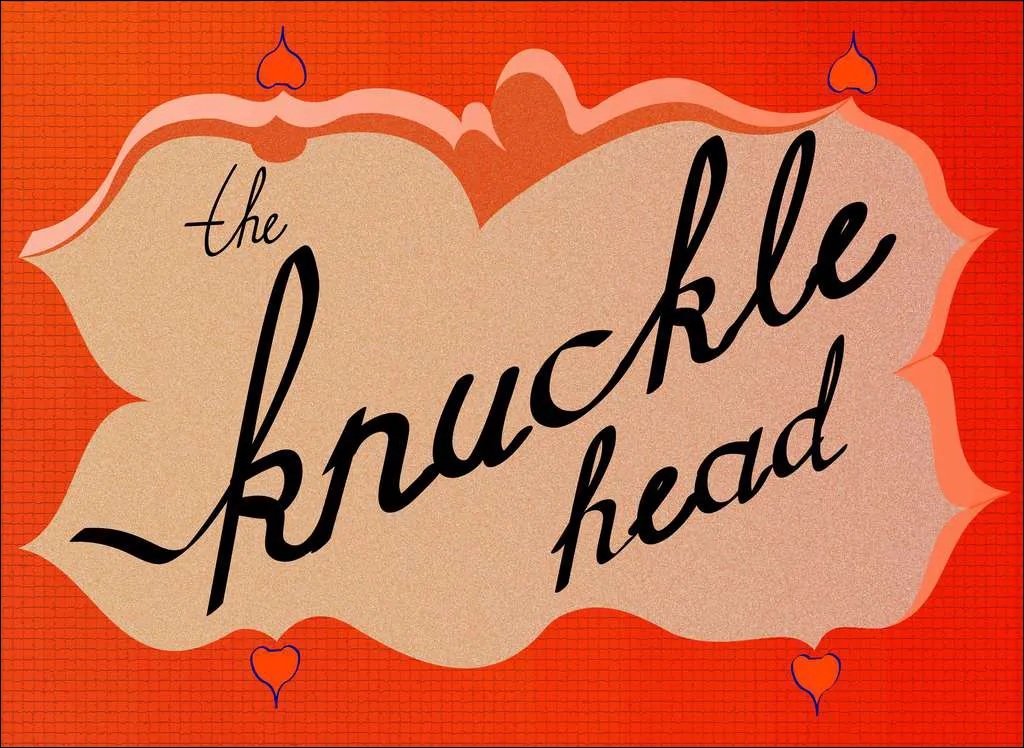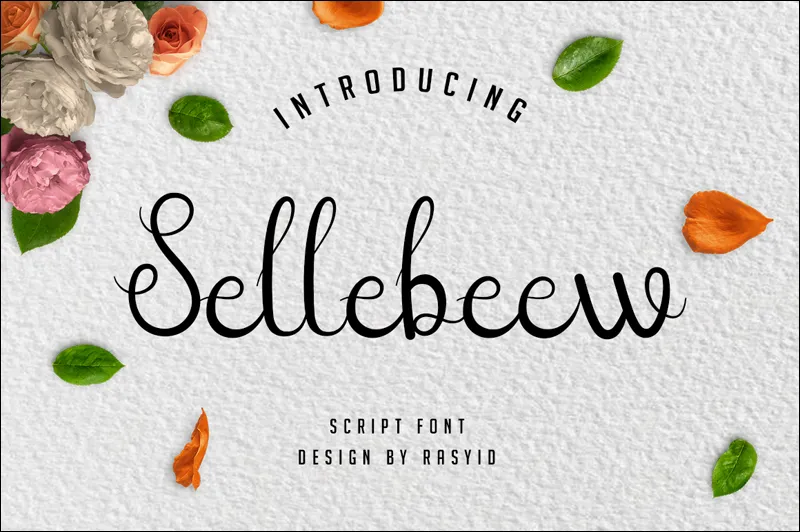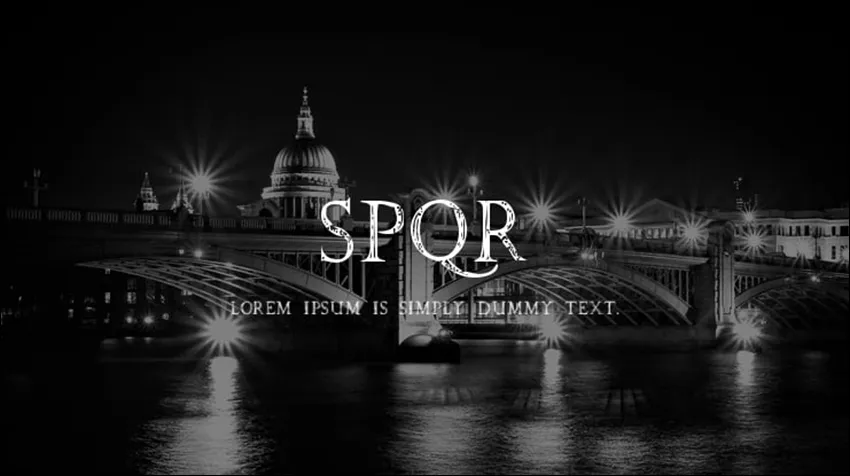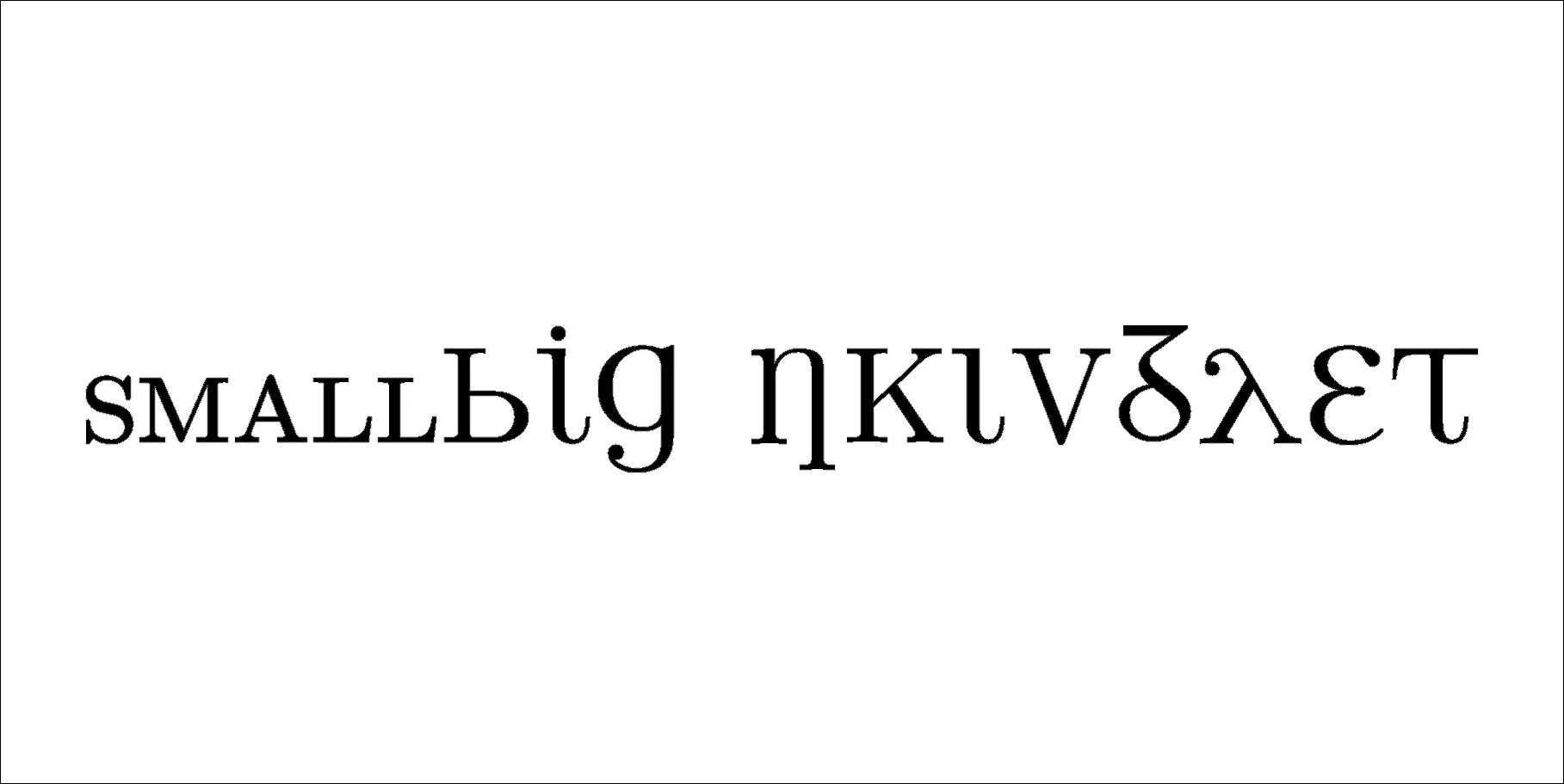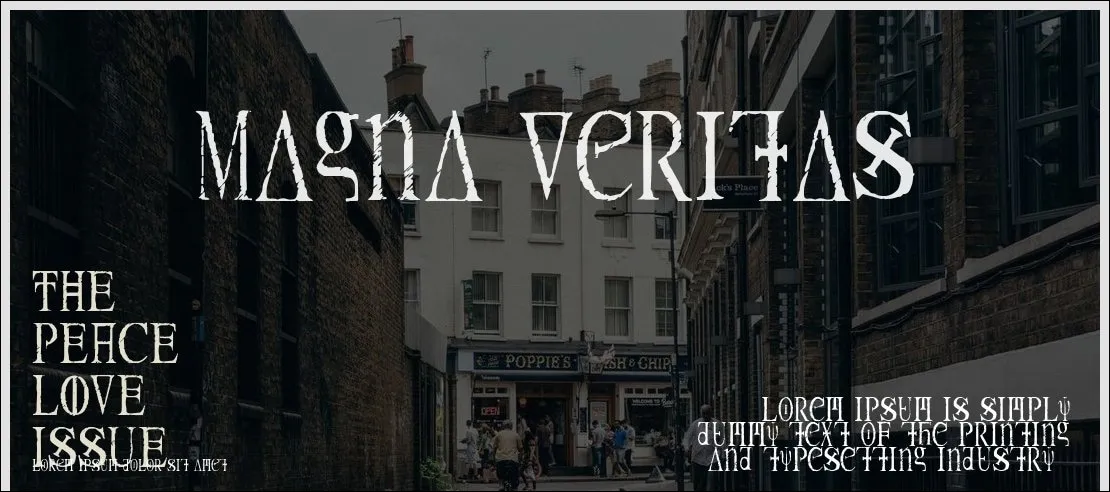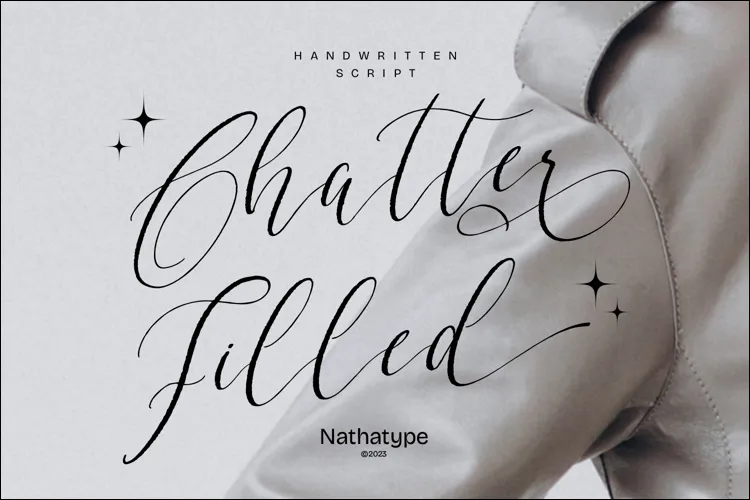
Font Latin telah menjadi primadona di kalangan desainer grafis. Bentuknya yang tidak biasa membuat font Latin sangat disukai dan digunakan dalam berbagai proyek desain. Tidak hanya membawa pesan yang jelas dan mudah dibaca, tapi font Latin juga menambahkan nuansa artistik dan keindahan visual pada setiap desain.
Dengan keanekaragaman gaya dan karakter, font Latin cocok digunakan dalam berbagai proyek desain, mulai dari pembuatan poster, logo, brosur, sampai desain branding dan lain-lain. Nah, apabila Anda sedang mencari font Latin gratis, dalam artikel ini, kami telah merangkum 39 macam font latin aesthetic dan keren, yang bisa langsung Anda download secara gratis. Yuk, kita lihat daftarnya di bawah ini!
Font pertama adalah Youth Touch, font latin dengan desain brush dan bentuk yang modern. Cocok digunakan untuk proyek desain yang ingin menampilkan kesan muda dan segar, seperti poster acara musik atau promosi produk untuk generasi muda.
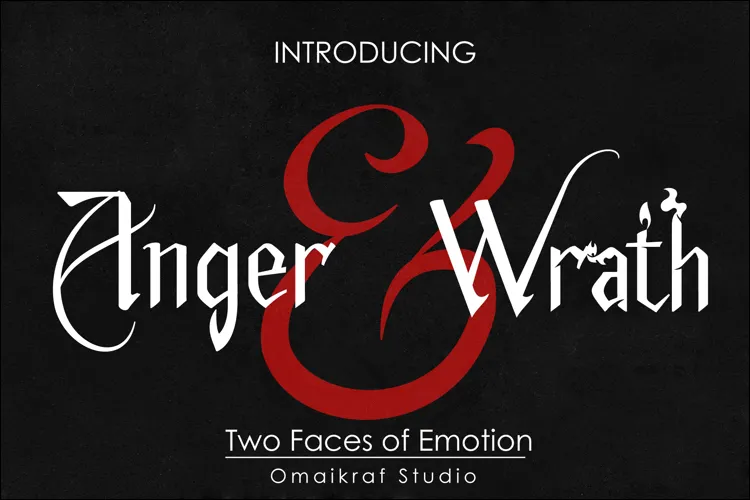
Font kedua adalah Anger & Wrath, dua jenis tipografi latin dengan tambahan gaya ornamen api di setiap ujungnya. Cocok untuk desain poster, flyer, brosur, undangan, dan lain-lain.
Font ini memiliki desain klasik dengan sentuhan artistik yang khas, cocok untuk proyek desain yang membutuhkan nuansa elegan dan vintage seperti undangan pernikahan atau logo bisnis.
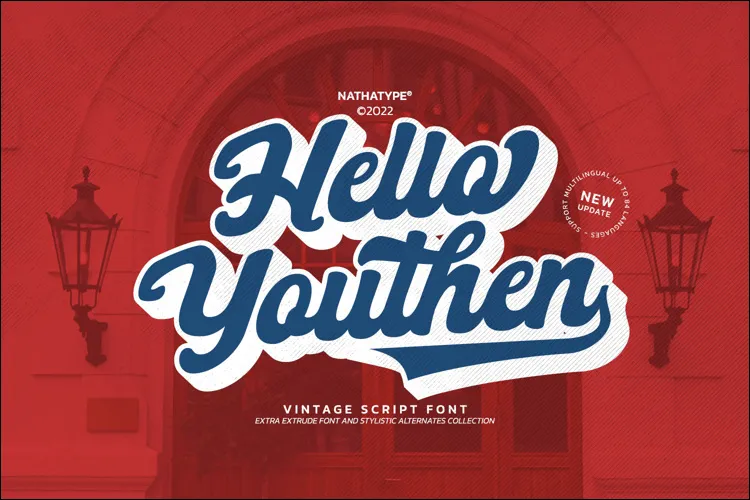
Sebagaimana namanya, font ini memiliki kesan anak muda dengan bentuk huruf yang tebal, cocok untuk proyek desain kartu ucapan atau poster perayaan.
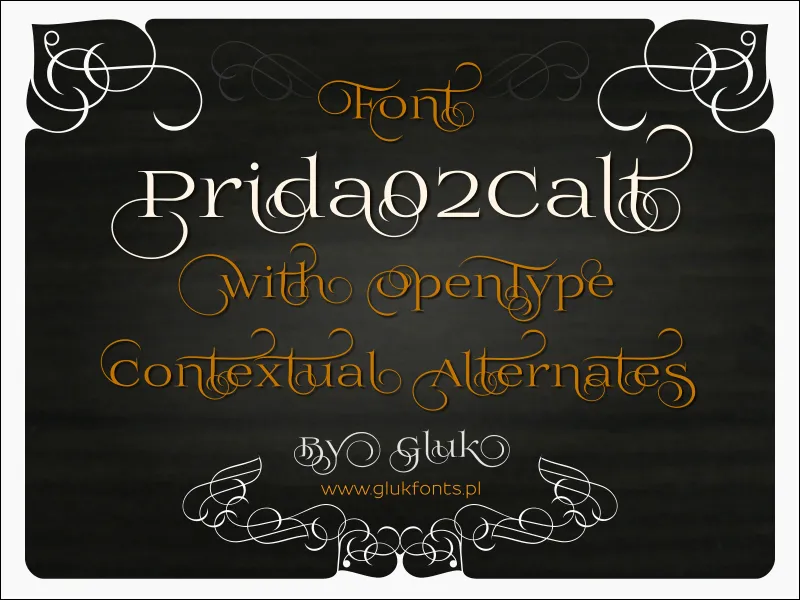
Font ini menampilkan gaya klasik namun tetap terlihat kontemporer, cocok untuk proyek desain yang menginginkan kesan yang berkelas namun tetap up-to-date seperti desain logo perusahaan atau kop surat.
Calditta merupakan font dengan desain yang simpel namun elegan, sangat sesuai untuk proyek desain yang membutuhkan kesan yang bersih dan profesional seperti brosur perusahaan atau materi presentasi.
Font ini memiliki gaya yang playful dan unik, cocok untuk proyek desain yang ingin menarik perhatian seperti poster promosi acara atau desain packaging produk yang ingin mencuri perhatian di rak toko.
Font ini memiliki desain yang halus dan elegan, cocok untuk proyek desain yang mengutamakan keindahan dan kemewahan seperti desain logo hotel mewah atau label produk skin care.
King Throne merupakan font latin yang mewah dengan desain tebal di setiap ujung karakternya, ideal untuk proyek desain yang ingin menampilkan kesan tegas dan berani seperti desain poster konser rock atau lainnya.
Font ini memiliki gaya yang cantik dengan garis-garis tipis di setiap hurufnya, cocok untuk proyek desain yang ingin menonjolkan energi positif seperti desain merchandise untuk acara komunitas atau banner promosi untuk toko kreatif.
Long Idea merupakan font latin tegak bersambung dengan desain tipis yang unik dan kreatif, sangat cocok untuk proyek desain yang ingin menonjolkan gagasan-gagasan baru dan inovatif seperti desain buku tahunan sekolah atau blog tentang kreativitas.
Kabyah merupakan font latin arabik dengan desain yang eksentrik dan artistik, cocok untuk proyek desain islami, seperti poster bulan ramadhan, idul fitri, dan lain-lain.
Breathy Signature merupakan font latin dengan gaya tulisan tangan yang indah dan feminin, sangat sesuai untuk proyek desain yang ingin menampilkan sentuhan personal dan romantis seperti desain kartu ucapan atau label produk kecantikan.
Font ini memiliki ujung karakter yang panjang dengan desain yang simple namun mewah, cocok untuk proyek desain yang ingin menampilkan kesan glamor dan eksklusif seperti desain kemasan parfum, make up, dan lain-lain.
Calledliner merupakan font dengan desain linier tipis tegak bersambung, sangat cocok untuk proyek desain yang mengutamakan kesederhanaan dan ketegasan seperti desain identitas merek.
Font latin modern dengan karakter yang rumit namun tetap unik, ideal untuk proyek desain kartu undangan atau layout majalah fashion.
Font ini memiliki desain brush dengan gaya tulisan tangan yang modern dan elegan, cocok untuk berbagai proyek desain seperti desain banner iklan online, pamflet promosi, packaging, dan lain-lain.
Smiling Lovely merupakan font desain brush yang elegan, berkelas, dan modern dengan karakter tulisan tangan yang menonjol, sangat sesuai untuk proyek desain yang ingin menampilkan kesan yang ceria dan optimis seperti desain merchandise anak-anak atau kemasan produk.
Font ini memiliki desain segar dan modern dengan gaya kaligrafi, cocok untuk proyek desain yang ingin menampilkan kesan kebersihan dan kesehatan seperti desain label produk organik atau brosur klinik gigi, dan lain-lain.